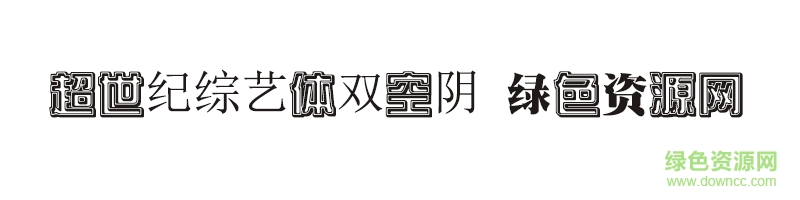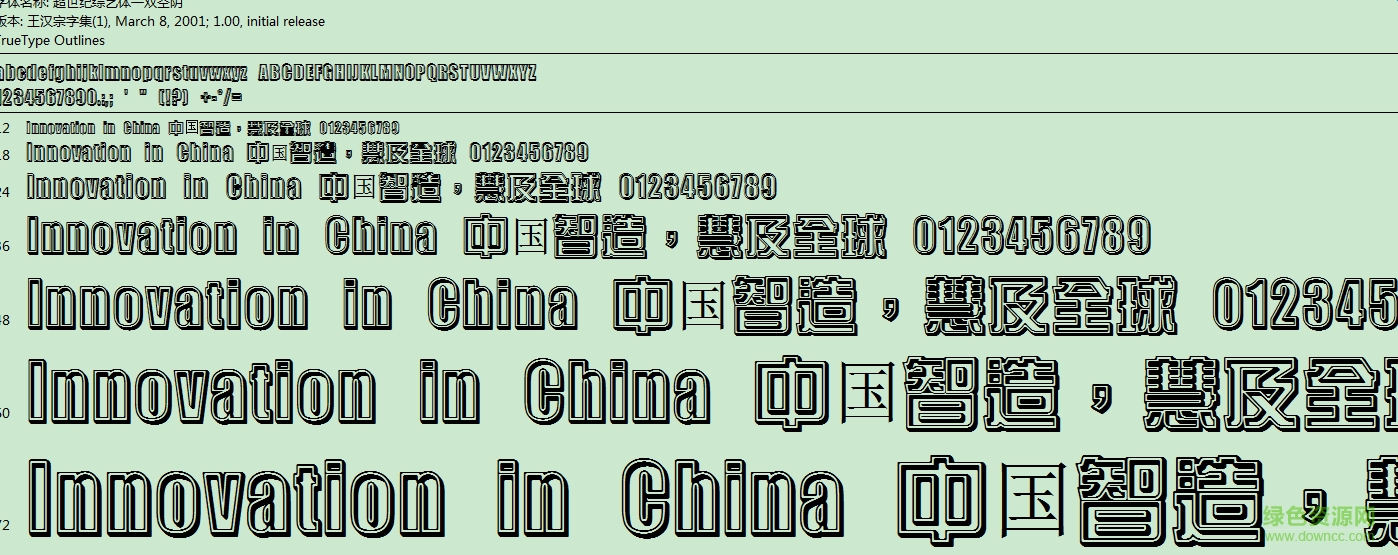
超世紀(jì)綜藝體雙空陰是一款非常有趣的字體,看起來就像是立體字一般,通過空白與黑色描邊為大家?guī)砹Ⅲw的感覺,非常適合用于廣告設(shè)計(jì)、藝術(shù)設(shè)計(jì)。大家快來綠色資源網(wǎng)踴躍下載吧!
超世紀(jì)綜藝體雙空陰是一款由超世紀(jì)綜藝體為原形再加工的藝術(shù)字體,空心字體效果震懾,非常引人注目,整體效果十分出色可應(yīng)用于多個(gè)行業(yè)。